Тенденции в типографике развиваются стремительнее, чем многие другие тенденции в дизайне. Ассортимент и разнообразие веб-шрифтов открывают интересные возможности для дизайна, а также новые визуальные сочетания. В этой статье мы поделимся с вами трендовыми сочетаниями шрифтов и примерами, как их использовать.
Сочетание шрифтов — это объединение разных шрифтов в одном дизайн-проекте. У хорошей пары шрифтов обычно не более двух-трех начертаний — такое количество выглядит гармонично и помогает создать достаточный контраст между стилями букв.
Пары шрифтов часто передают похожее настроение, а их формы дополняют друг друга — именно поэтому такие сочетания обычно привлекает внимание пользователей, а не конкурируют между собой.
Несмотря на то, что используется термин «пара», вы можете использовать несколько шрифтов в одном проекте. Есть одно правило, которого следует придерживаться — в паре должен быть один акцентный шрифт. Эта техника помогает сделать текст более читаемым, а также создать нужный баланс.
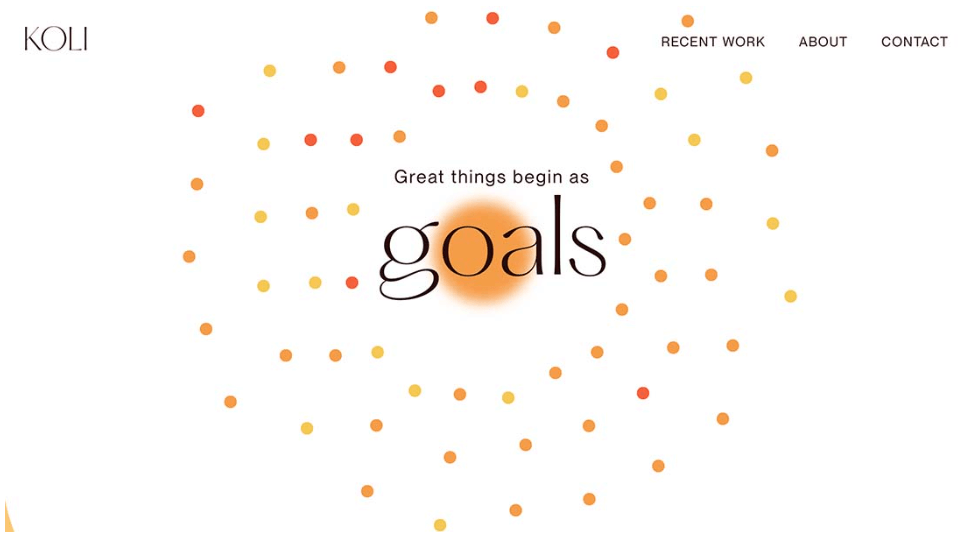
Сочетание простого шрифта без засечек с тонким современным шрифтом с засечками выглядит очень элегантно, стильно и эффектно.
Чаще всего современные шрифты с засечками выглядят неразборчиво, но если использовать их в буквах крупного размера и всего для нескольких слов — это будет гармонично. В примере выше используется необычный шрифт Hatton, который в сочетании с анимацией выглядит очень эффектно.
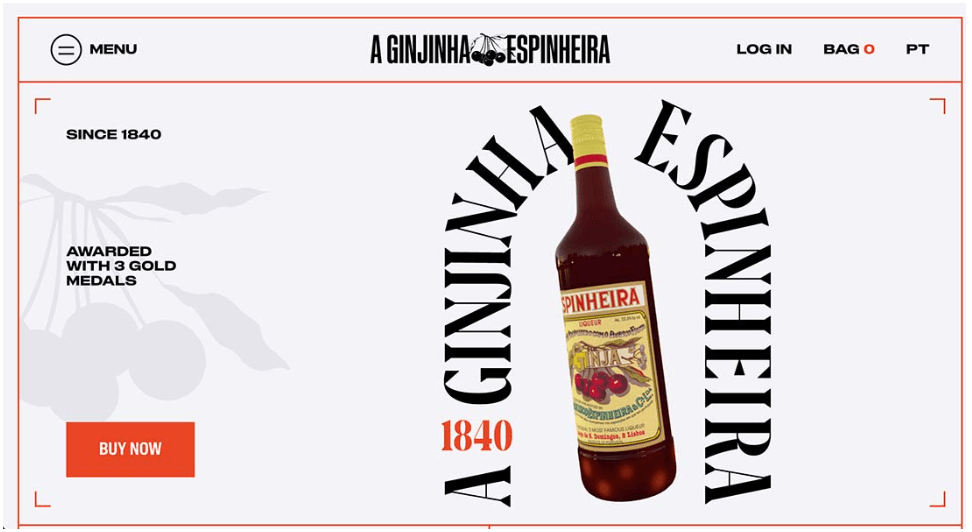
Сочетание 3-х шрифтов, каждый из которых имеет жирное начертание — это очень смелая тенденция. В дизайнах это выглядит эффектно, потому что каждый шрифт в проекте выделяется.
Используя это сочетание, в других элементах дизайна мы рекомендуем придерживаться минимализма — фон, акценты, цвета. Так вы сможете создать пространство и легкость между элементами.
В примере выше используется три варианта жирного шрифта: для брендинга центрального заголовка (сжатый шрифт без засечек), для арки вокруг бутылки (жирный шрифт с засечками), для всех остальных текстовых элементов (жирный шрифт без засечек). В сочетании все это выглядит очень гармонично и стильно.
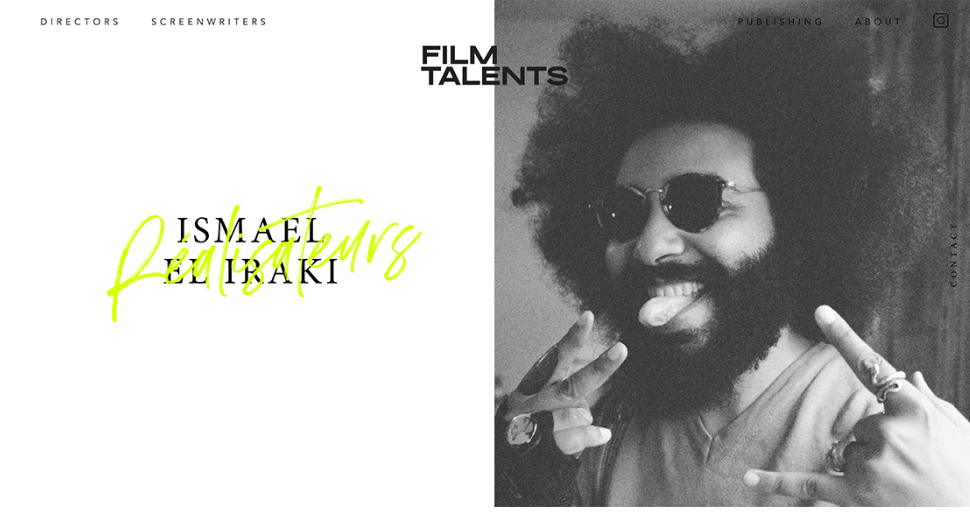
Шрифты с рукописными элементами сочетаются практически с любым другим стилем типографики — они помогают создать особенные и эффектные дизайн-проекты.
В примере выше рукописный шрифт не только располагается на главном экране, он еще и анимируется — это создает впечатление, что надпись появляется в реальном времени. При нажатии на элементы в навигации возникает еще один интересный рукописный элемент.
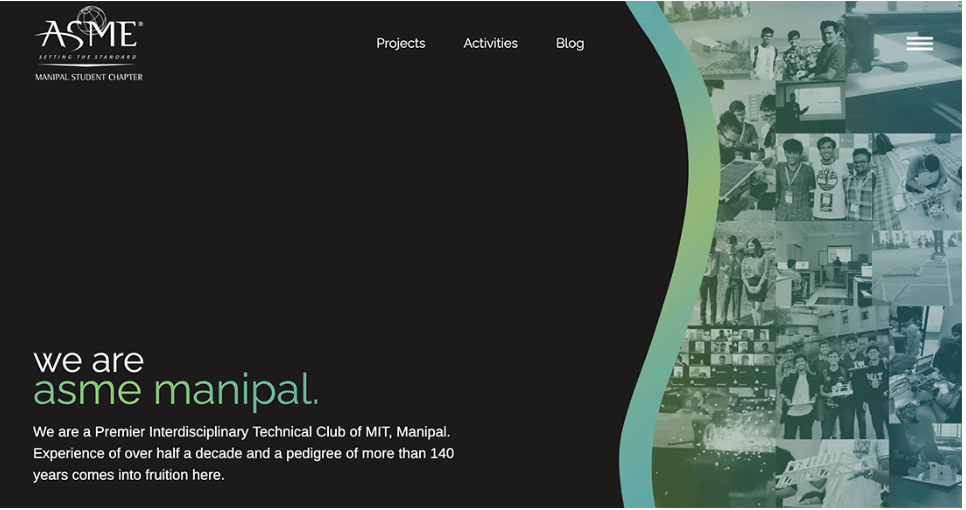
Сочетание одноцветного шрифта с градиентным шрифтом — еще один тренд нового года. Элемент градиента используется повсюду — для текстов, элементов кнопок и даже в качестве фона.
В примере выше градиент перемещается внутри букв и создает ощущение плавного потока и движения. Большинство текстовых пар с градиентным шрифтом чаще всего используют заглавные буквы для этих слов. В этом же дизайне использованы маленькие буквы, что тоже выглядят эффектно — дизайн получается легким и не перегруженным.
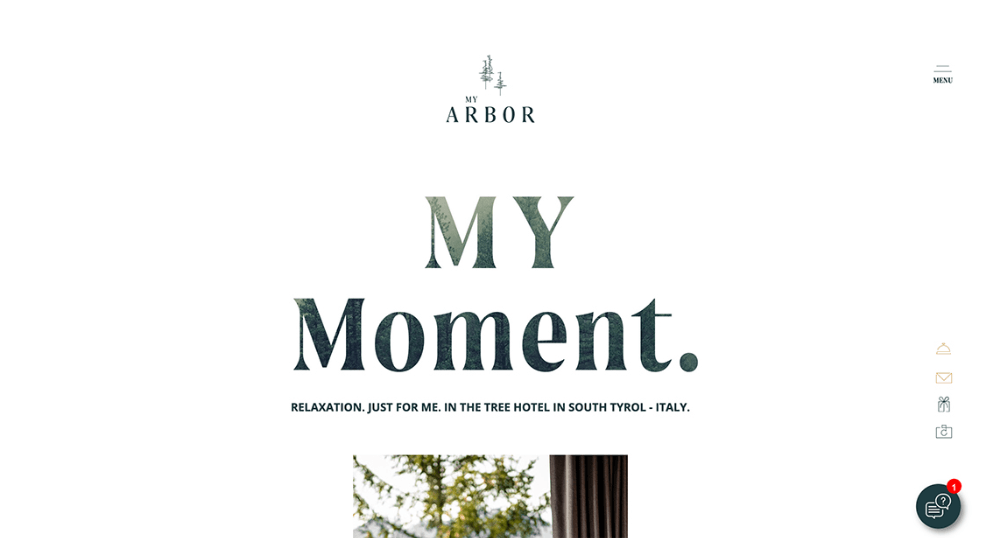
Сочетание шрифтов с засечками и без засечек хорошо работает с буквами крупного размера и минимальным количеством текста. Помните, что текст с заглавными буквами часто выглядит перегруженным, если его слишком много.
Мы рекомендуем использовать эту тенденцию для коротких заголовков и второстепенных текстов, которые занимают одну строку, как в примере выше.
Мы также рекомендуем вам использовать этот тренд в сочетании со светлым фоном и темным текстом, чтобы создать необходимый контраст.
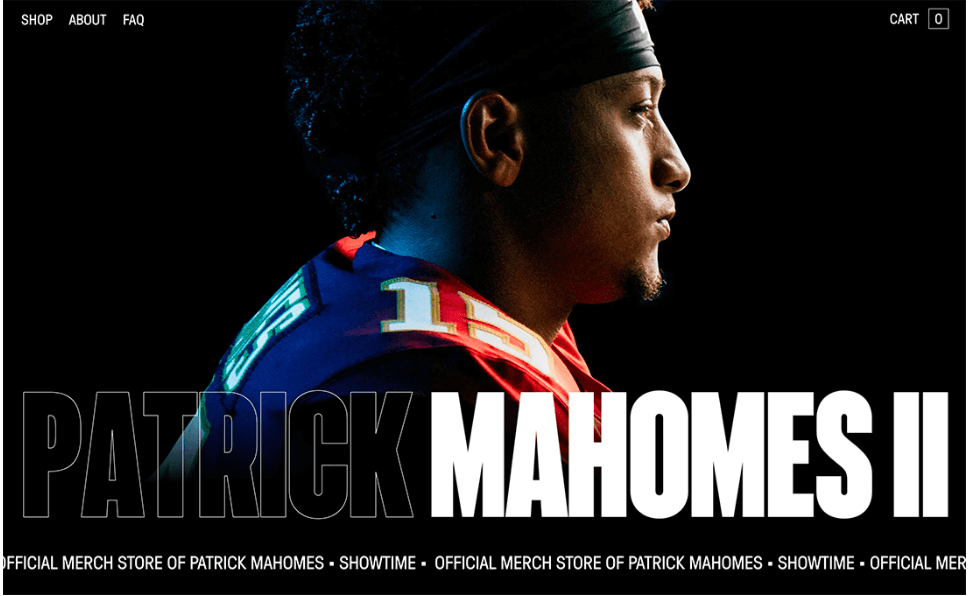
Одна из самых интересных тенденций в типографике в 2023 году — это контурные шрифты. Сочетание прозрачной заливки с контуром на фоновом изображении выглядит очень эффектно и необычно.
Контурный шрифт в дизайнах всегда выглядит акцентно — он поможет вам привлечь внимание пользователей. Контурный шрифт идеально работает практически с любым типом шрифта, но чаще всего его используют в сочетании со шрифтом без засечек — это помогает создать понятные и четкие контуры.
При работе с этой комбинацией шрифтов мы рекомендуем использовать заливку для важного текста, а контур оставлять для акцентного текста.